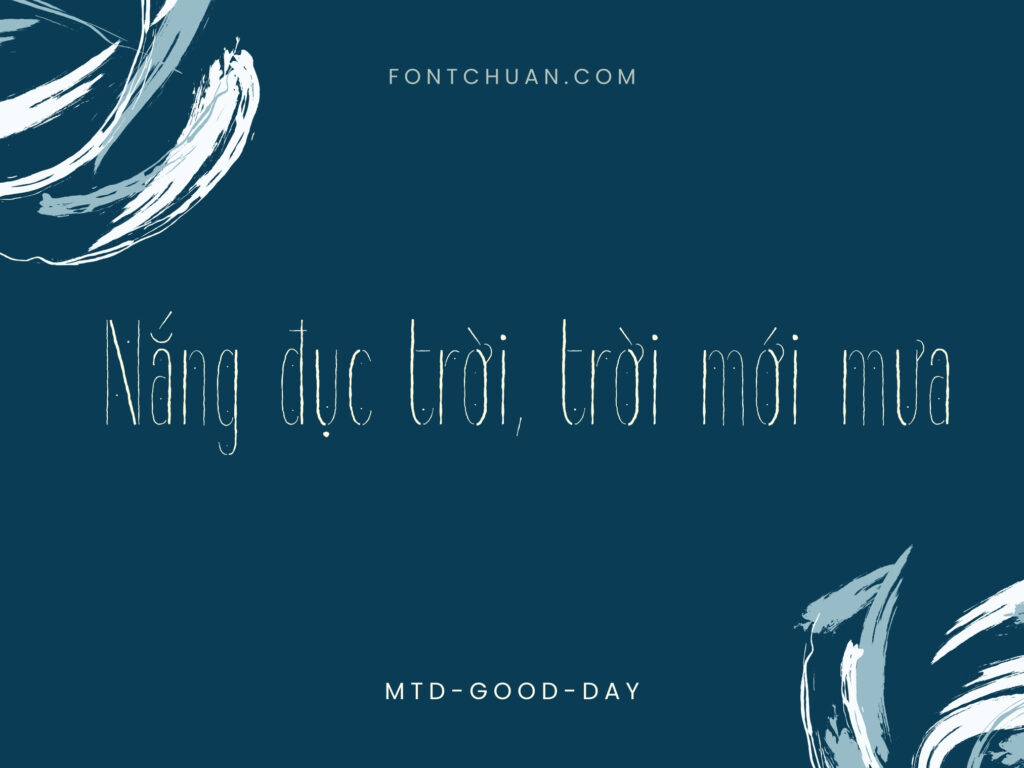
Font MTD Good Day Việt Hóa
Font MTD Good Day là một phông chữ viết tay ngọt ngào, được thiết kế với sự chăm chút tỉ mỉ để tạo ra những đường nét mượt mà và tự nhiên. Font đã được Việt hóa bởi Mộc Hạ, hỗ trợ tiếng Việt và hơn 90 ngôn ngữ khác, giúp mở rộng khả năng ứng dụng trong các thiết kế đa ngôn ngữ. Đây là một trong những phông chữ được cộng đồng thiết kế đánh giá cao và ứng dụng trong nhiều dự án sáng tạo, đáp ứng nhu cầu đa dạng của người dùng.
MTD Good Day nổi bật với các ký tự mềm mại, mang đến cảm giác thân thiện và gần gũi. Font rất phù hợp cho các thiết kế logo, thương hiệu cá nhân, thiệp mời, tiêu đề, bao bì sản phẩm và các ấn phẩm đòi hỏi sự tinh tế và cá nhân hóa. Các ngành nghề phù hợp bao gồm quảng cáo, giáo dục, công nghệ, thiệp cưới và ảnh cưới. Font này cũng lý tưởng cho các sự kiện như Tết, Giáng sinh, Valentine và các lễ hội khác.